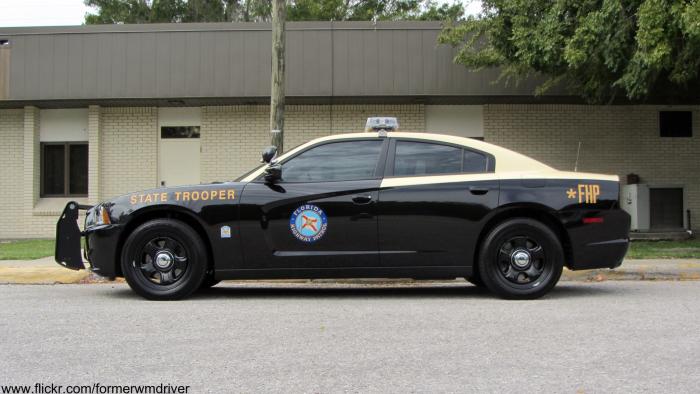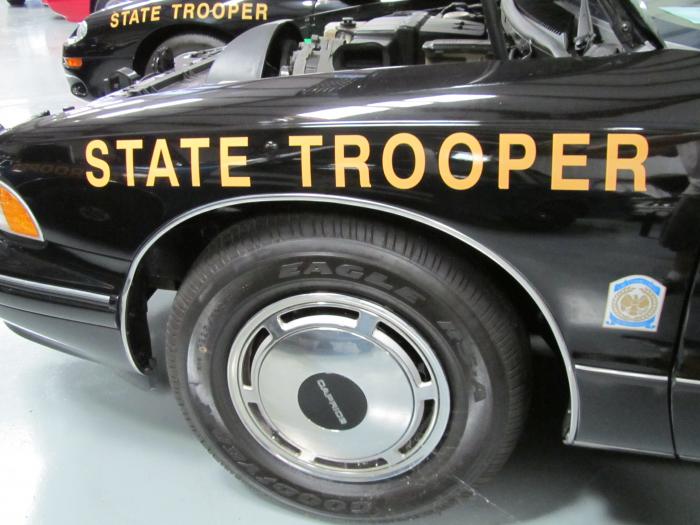
Schrift/Buchstaben gesucht
Hallo..Ich suche einen Schriffttyp den ich partou nicht finde..
Calibri (fett) sowie Kartika kommen da schon nahe dran...aber das "R" ist irgendwie anders.
Anbei Bild vom Schriftzug
Hmmm..jetzt fehlt mir nur noch das  * FHP am Fahrzeugheck(siehe Bild)
weiß nicht ob das ein eigener Schrifttyp ist oder ob man da irgendwas "gestreckt" hat.
Ist für einen Nachbau (Filmfahrzeug) und sollte schon recht autentisch sein.."Kritiker" sehen doch bekanntlich das kleinste Detail.. :-o
Hast aber recht..das F fluchtet so mit dem H nicht...mal sehen ..
Das Vorlagenbild war wahrlich etwas klein aber bei Flickr fand ich dieses Bild. Mir erschien es zwar als wären die Querbalken des „F“ etwas länger, aber das kann auch täuschen bzw. läßt sich eventuell mit einem Vektorgraphikprogramm korrigieren.
Ich habe ja heute schon an anderer Stelle drüber geschrieben: Oft ist eine schnelle Lösung nicht, nach einen passenden Font zu suchen, sondern das Logo einfach schnell nach zu zeichnen. Ich habe das mal getan:
Ich habe auch einen Font 'draus gemacht, darin ist auf A das komplette Logo, einzeln geht es auch über *FHP
*FHP ist übrigens eine Telefonnummer der floridianischen Autobahnpolizei.